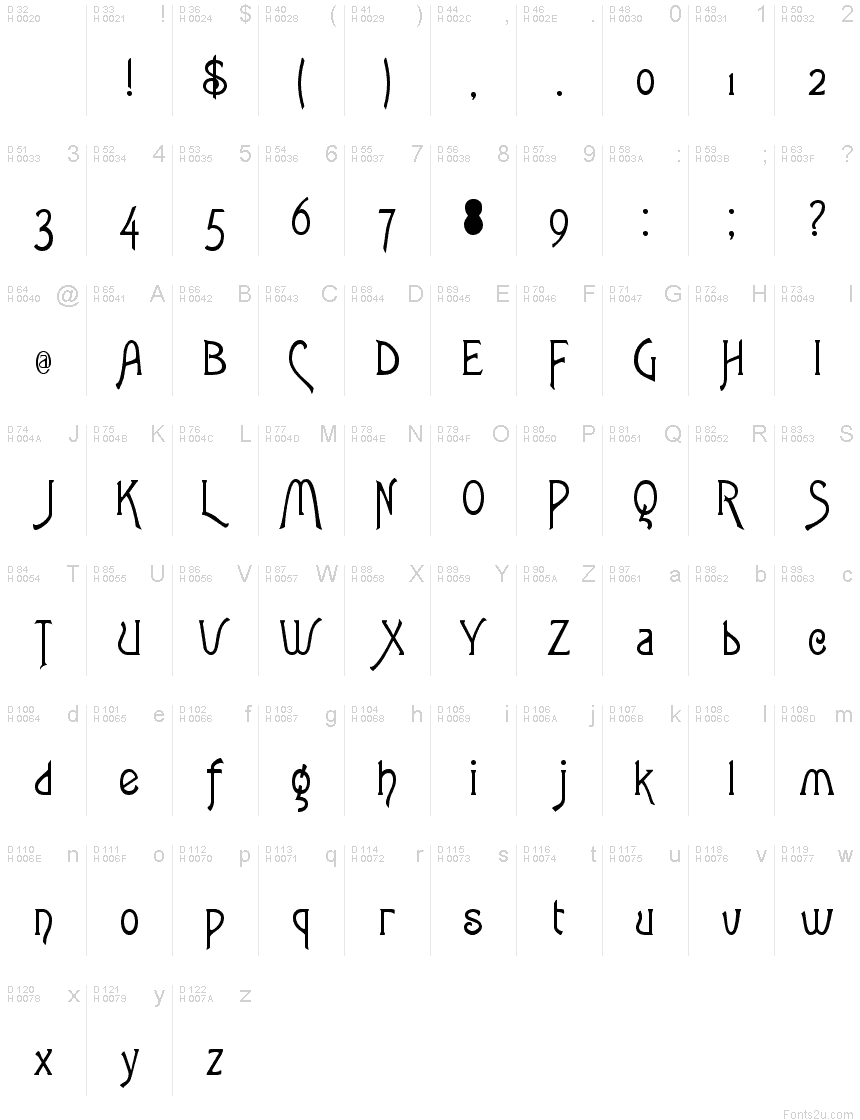
Parsnip to bezpłatny krój pisma typu display w stylu retro, wyróżniający się wysokim kontrastem kresek. Długie pionowe linie i zamaszyste łuki nadają literom secesyjny charakter, podkreślony delikatnie rozszerzającymi się łączeniami i nietypowymi, otwartymi formami.
Doskonale sprawdza się na plakatach o wysmakowanym, historycznym klimacie. Ta sama dekoracyjna konstrukcja pasuje do okładek książek, eleganckich opakowań butikowych oraz materiałów graficznych na wydarzenia inspirowane wzornictwem z przełomu wieków. Krój najlepiej prezentuje się w wyrazistych nagłówkach, gdzie wydłużone sylwetki liter same w sobie stają się ozdobą.